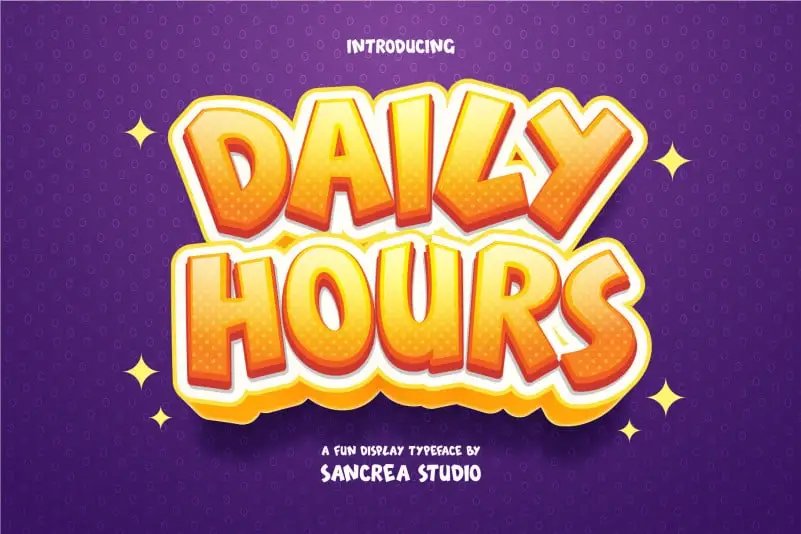
Daily Hours Display Font – Download Grátis
A Daily Hours Display Font é uma escolha perfeita para quem procura algo divertido e descontraído no ambiente da tipografia. Composta por letras a mão-dura com traços fortes, esta fonte faz mais do que simplesmente dar um toque criativo; ela eleva seu uso de forma elegante, ideal tanto para aplicações visuais como logotipos quanto para textos legais e informativos. Seja você quem está planejando criar um design alegre para uma identidade visual ou quem está buscando uma maneira divertida de trazer vida à sua página web com frases inspiradoras, essa fonte é perfeita. Ela destaca-se por seu uso contínuo dos caracteres maiúsculos e sua inclusão da numeração e pontuação, garantindo que sua mensagem seja clara e fácil de entender. Seja você um criador de logotipos, designer gráfico ou até mesmo uma escritora blogueira, Daily Hours Display Font pode tornar suas criações ainda mais vibrantes. Seu estilo inovador e colorido a torna uma excelente opção para apresentações de slides, sites pessoais ou qualquer outro projeto que você possa estar desenvolvendo. Não deixe de adicionar um toque único à sua próxima produção com Daily Hours Display Font.